小さなひとマスが楽しくなる♪絵日記レイアウト11のアイデア
今回はひとマス絵日記の楽しみ方「イラストと文字のレイアウト11パターン」をご紹介します。
月間手帳やカレンダーの小さなひとマスに、1日1絵を描いて楽しむ「ひとマス絵日記」。
ちょっとした配置や描き方を変えるだけで、いつもの絵日記がぐっと楽しくなります。
ひとマス絵日記ってこんなの
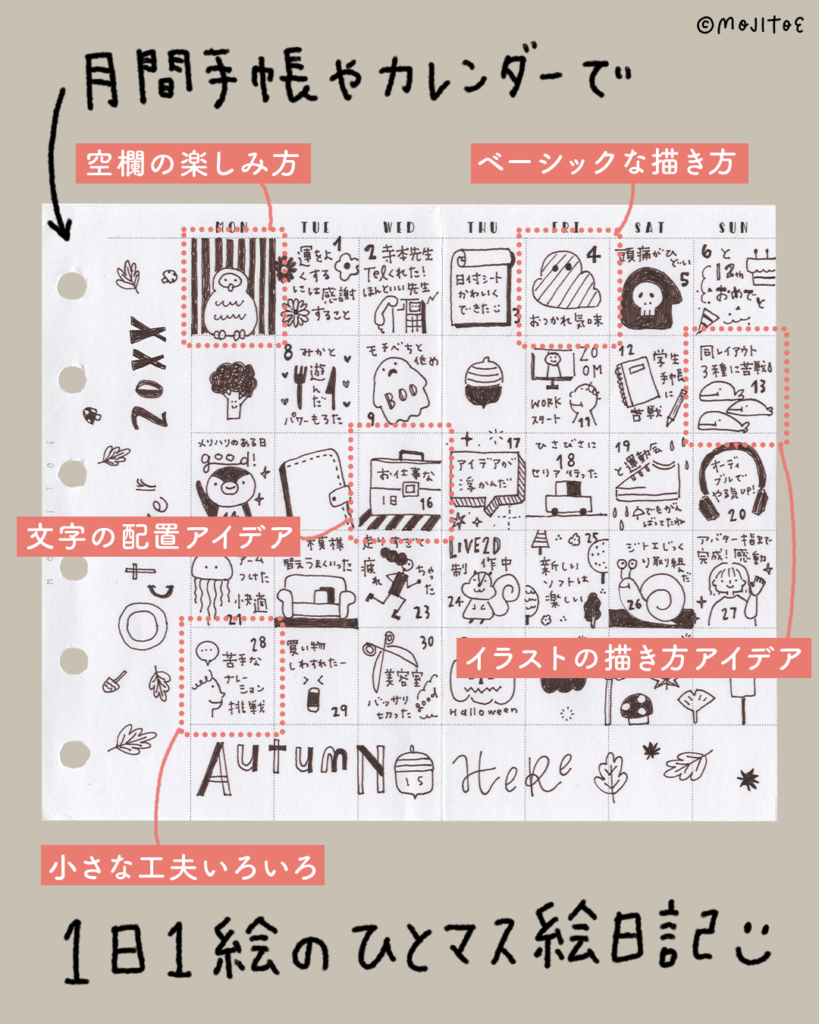
小さなスペースに、今日を描く。
月間手帳やカレンダーの「ひとマス」。
ほんの小さなスペースだけど、イラストと文字を少し工夫するだけで、ぐっと楽しくなります。
「絵日記を書いてみたい人」
「書いているけど、いつも同じになってしまう人」
そんな方に向けた、眺めるだけでも楽しいアイデア集です。
ベーシックな描き方
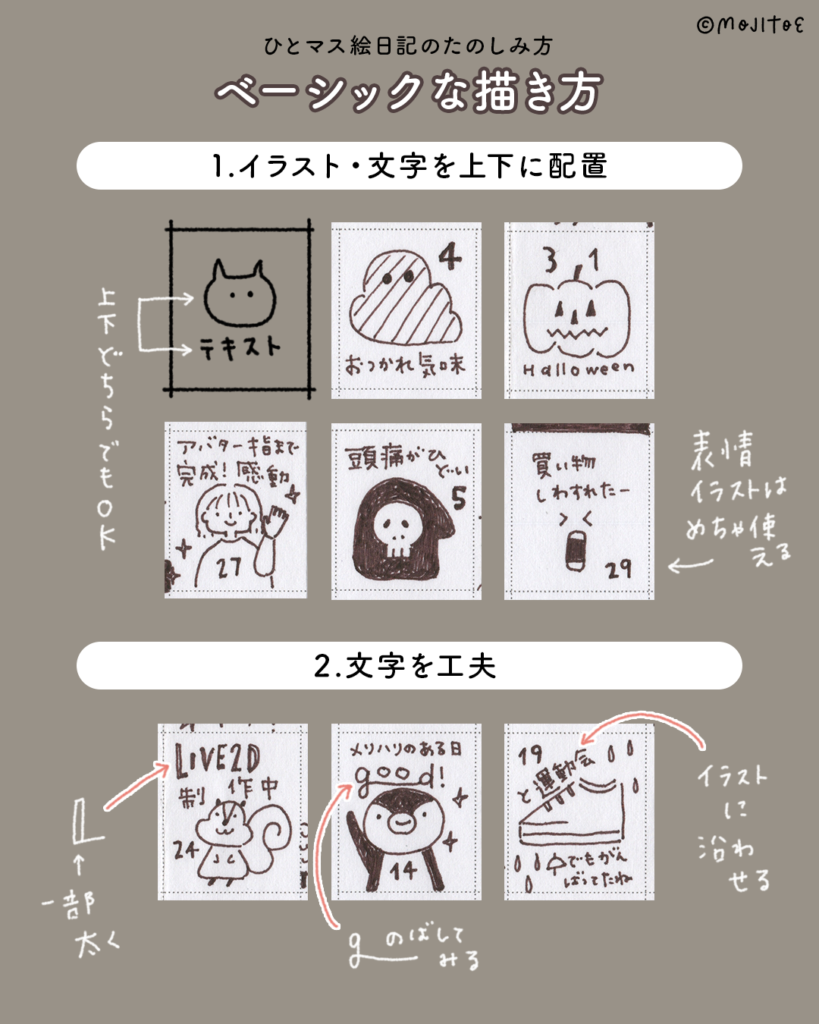
1. イラストと文字を上下に配置
ひとマス絵日記でまず試してほしいのが、イラストと文字を上下に配置する描き方です。
イラストが上でも、文字が上でも、どちらでも問題ありません。その日の気分や、描きたい内容に合わせて自由に決めてOKです。
迷ったときは、表情だけのイラストがおすすめです。顔だけでもその日の雰囲気が伝わりやすく、小さなマスでも描きやすいので、ひとマス絵日記と相性がとてもいい描き方です。
2. 文字をちょっと工夫する
文字だけの日でも、描き方を少し変えるだけで表情が生まれます。
すべて同じ太さで書くのではなく、一部を太くしてみたり、気持ちを込めたい言葉を少し伸ばして書いてみたりするだけでも印象が変わります。
また、イラストの形に合わせて文字を沿わせるように配置すると、全体がまとまりやすくなります。文字もレイアウトの一部として楽しんでみてください。
文字の配置アイデア
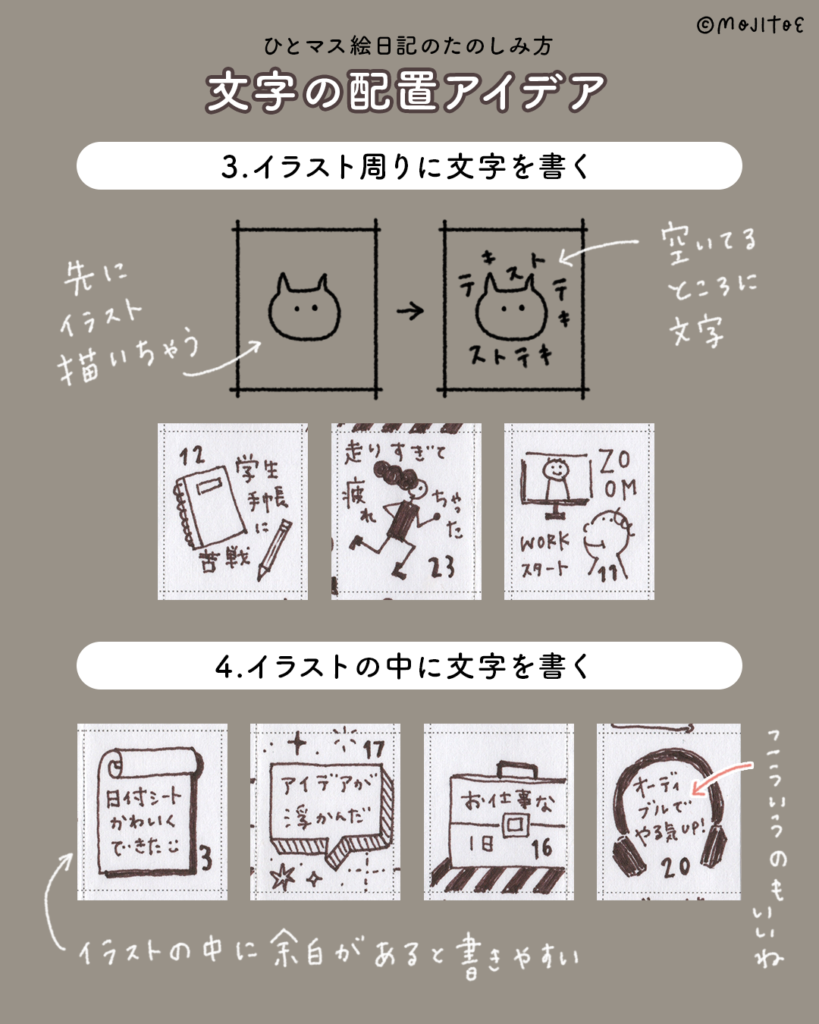
3. イラストの周りに文字を書く
文字の配置に迷ったときは、先にイラストを描いてしまうのもおすすめです。
イラストを描いたあと、空いているスペースに文字を書いていくと、自然なバランスでレイアウトしやすくなります。
スペースを埋める感覚で、文字を置いていくようなイメージです。
4. イラストの中に文字を書く
イラストの中に文字を書くのも楽しいアイデア。
イラストの中に余白があると、文字が書きやすくなります。
たとえば、メモ紙やカバンの中、ヘッドホンの内側の空間など。
イラストと文字が一体になり、まとまりのあるレイアウトになります。
イラストの描き方アイデア
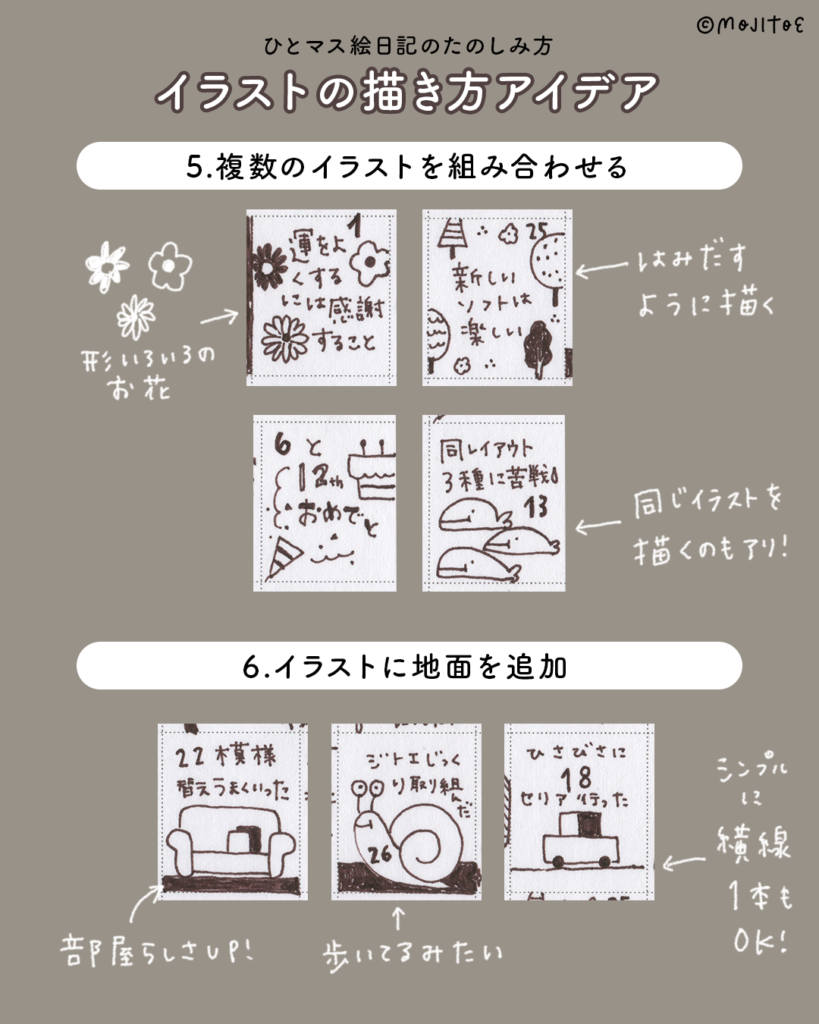
5. 複数のイラストを組み合わせる
ひとつのイラストだけでなく、複数のモチーフを組み合わせるのもおすすめです。
形の違うお花を並べたり、同じイラストを連続で描いたりすると、ひとマスの中でも動きが出ます。
マスから少しはみ出すように描くのも、空間の広がりが出てかわいい描き方です。
6. イラストに「地面」を足す
イラストに地面を描き足すだけで、ぐっと雰囲気が変わります。
ソファの下に床を描くと部屋らしさが出たり、カタツムリの下に線を引くだけで歩いているように見えたりします。
シンプルな横線一本でも、車のイラストなどが生き生きとした印象になります。
小さな工夫いろいろ
7. イラストの描き方
イラストは、きっちりまっすぐ描かなくても大丈夫です。
少し傾けて描いたり、下の部分が切れていてもOK。
8. 縦長のイラスト
縦長のイラストは文字を書く場所が狭くなりますが、文字のフレーズが途中で折り返しても気にしなくて大丈夫。ちまちまとした文字がとっても可愛い印象に。
9. 文字との組み合わせ方
文字の配置や書き方を変えることで、表現の幅が広がります。
一部を縦書きにしてみたり、モコモコしたふきだしを使ってみたり。
文字もイラストの一部として考えると、ひとマス絵日記がより楽しくなります。
空間の楽しみ方
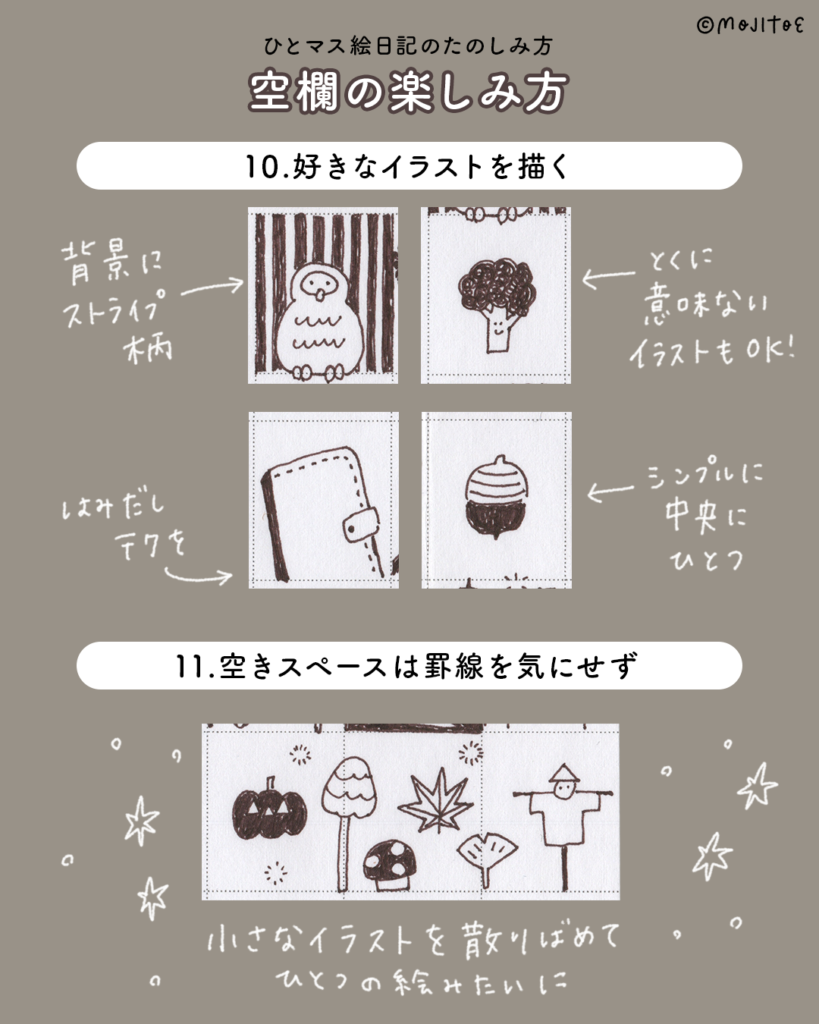
10. 好きなイラストを描く
書くことが思いつかない日も、ひとマス絵日記は楽しめます。
そんな日は、好きなイラストを描くだけでもOKです。
背景にストライプ柄を入れてみたり、特に意味のないモチーフを描いてみたり。
唐突なブロッコリーが登場する日があっても、それも絵日記の一部です。
中央にひとつだけ、ぽつんとイラストを描くのも、さりげなくてかわいい配置です。
11. 空きスペースは罫線を気にしすぎない
空きスペースが気になるときは、罫線にきっちり合わせなくても大丈夫です。
小さなイラストを散りばめて、ひとマス全体をひとつの絵のように仕上げるのも楽しい使い方。
自由に使うことで、ひとマス絵日記の楽しみ方はさらに広がります。
今回はひとマス絵日記の楽しみ方「イラストと文字のレイアウト11パターン」をご紹介しました。
小さなスペースだからこそ、気負わず、自由に、遊ぶように描いてみてください。